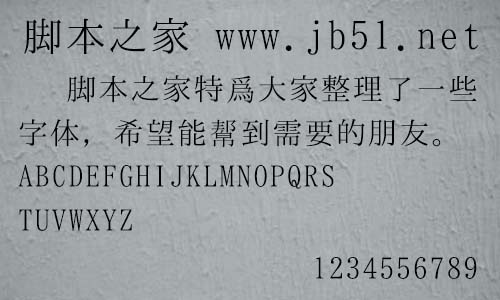
花漾明朝體HannariMincho是一款日系風(fēng)格的中文字體,這款字體筆觸較為纖細,字體清楚明朗,字形黑白空間結(jié)構(gòu)分明,適合應(yīng)用于藝術(shù)設(shè)計、平面宣傳設(shè)計、網(wǎng)頁設(shè)計,書法字帖等領(lǐng)域,需要的朋友可以前來本站下載。